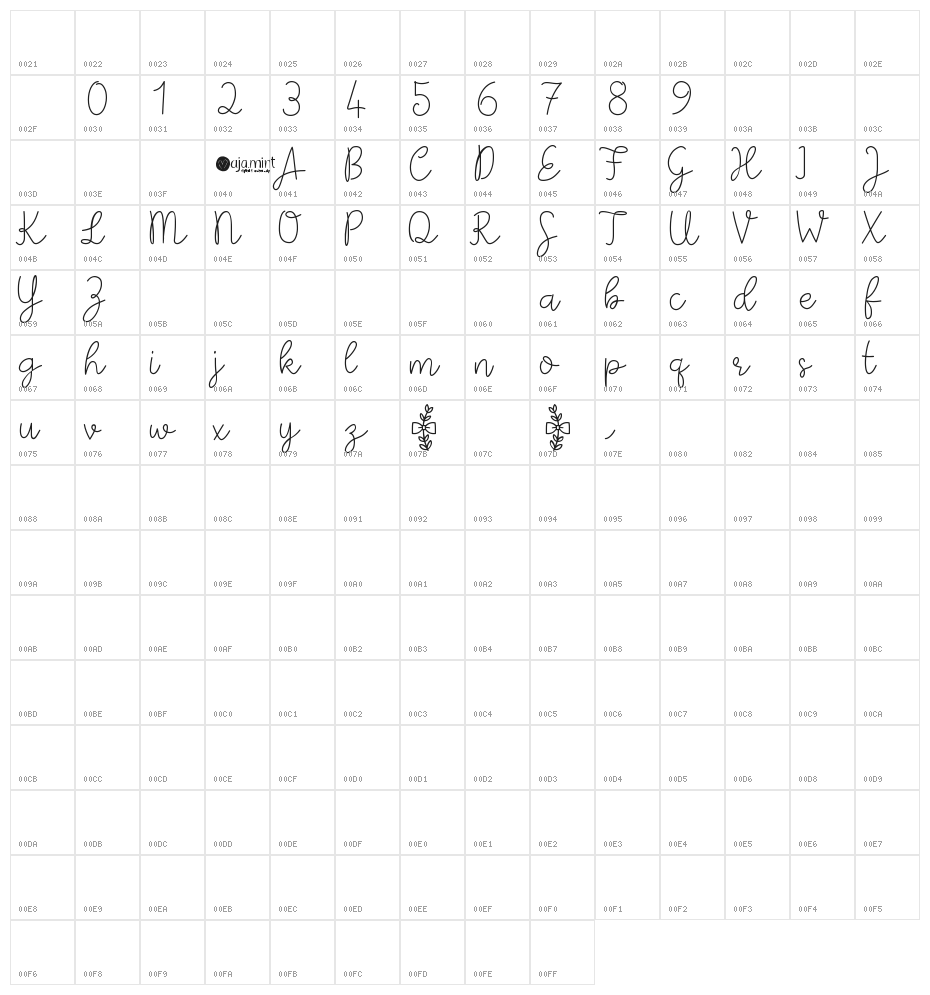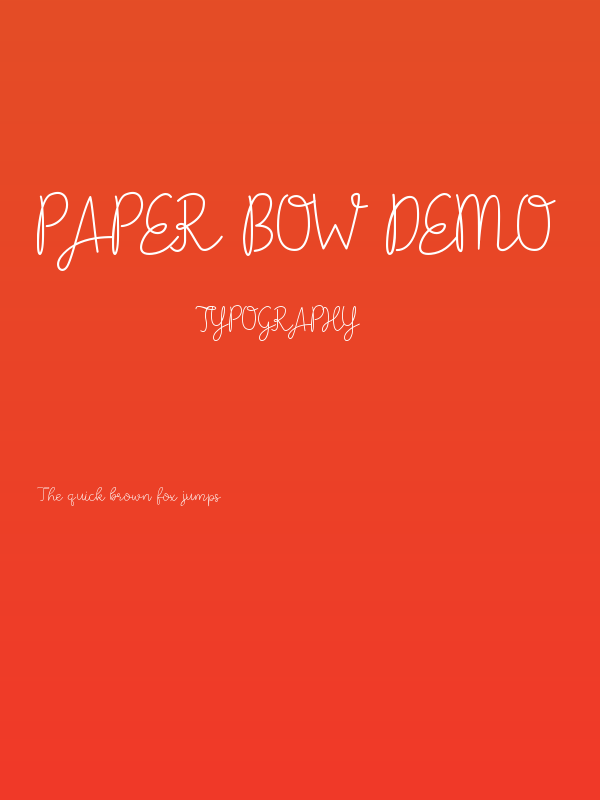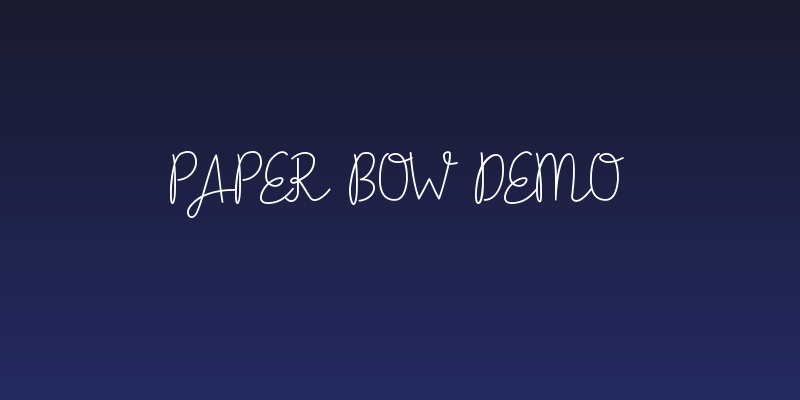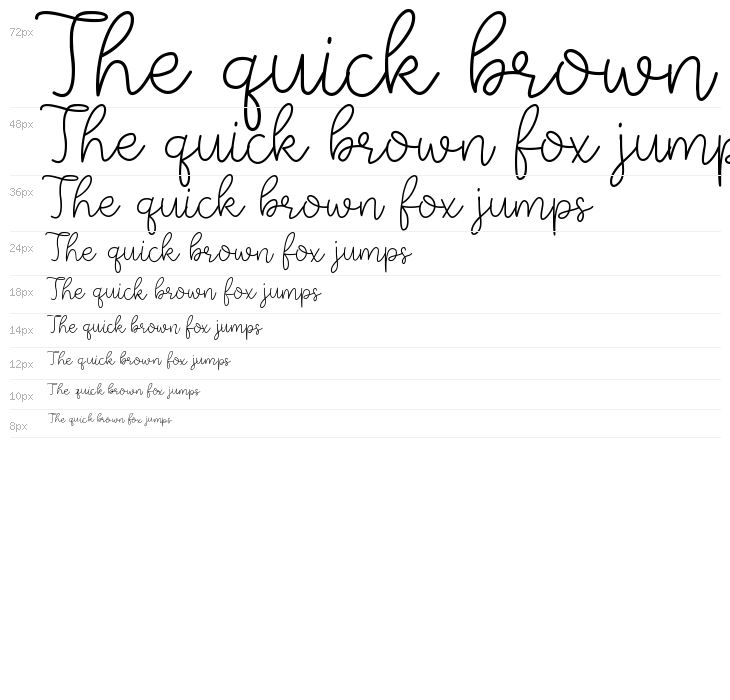
Paper Bow DEMO Font
| Caso d'uso | Logos, Invitations, Greeting cards |
| Progetti proposti | Ideal for wedding invitations, greeting cards, branding, and creative projects that require a touch of elegance. |